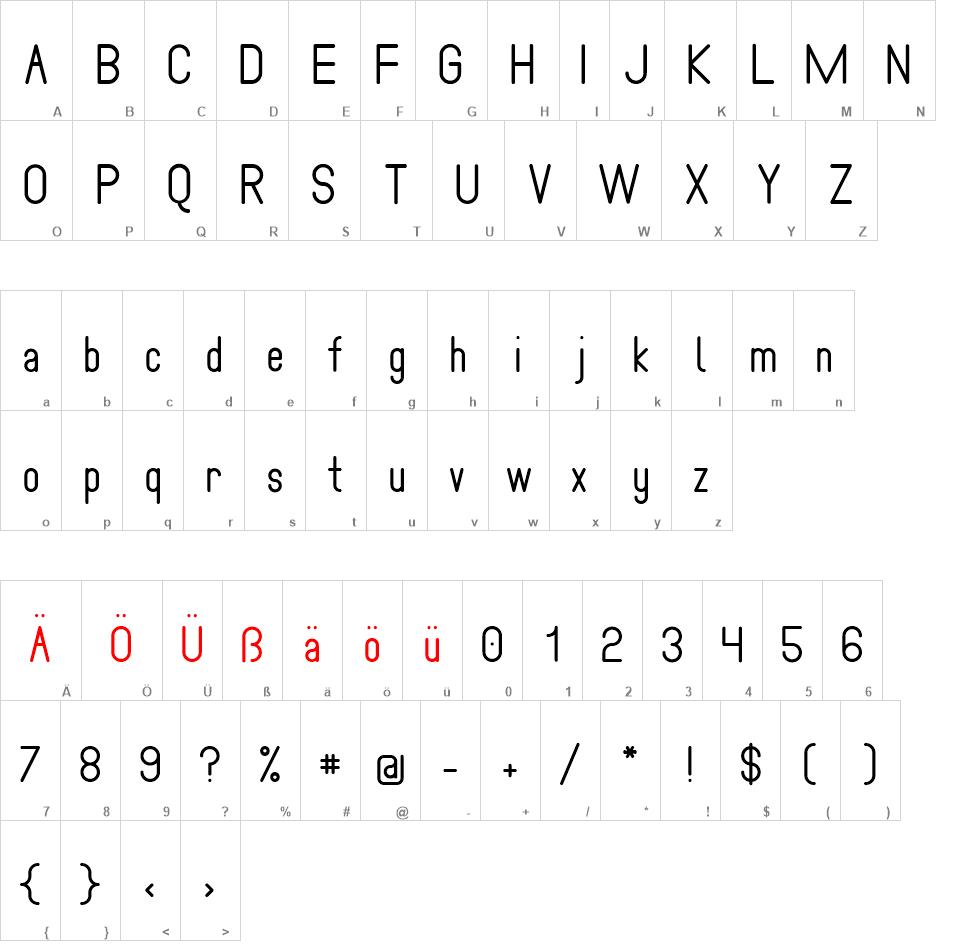
Pianaforma
Pianaforma ist eine Schrift, die durch eine sehr kleine Anzahl sehr einfacher rationaler Regeln erstellt wird, die sistematisch angewendet werden.
Ihr Ziel ist es, eine mögliche Darstellung der gemeinsamen Idee des Alphabets zu zeigen.